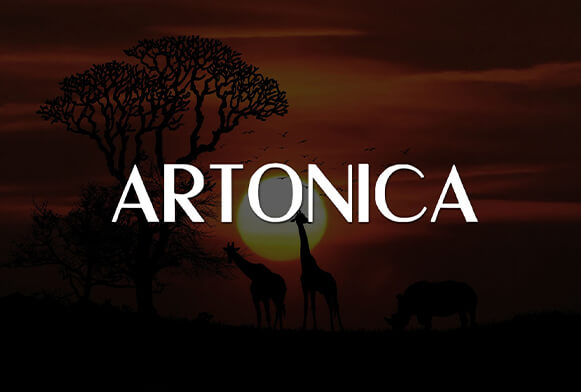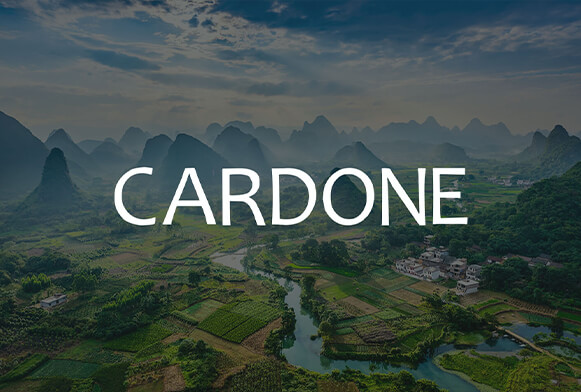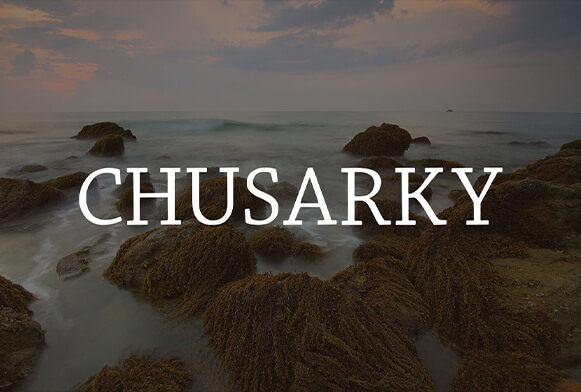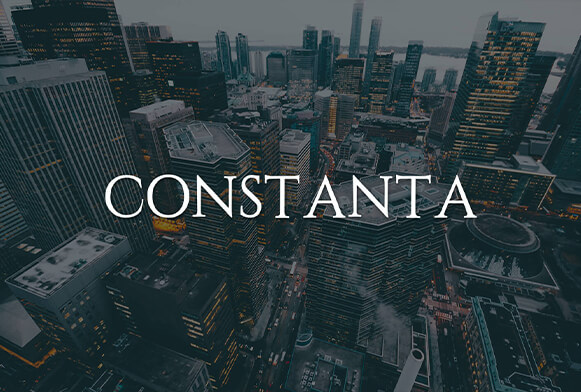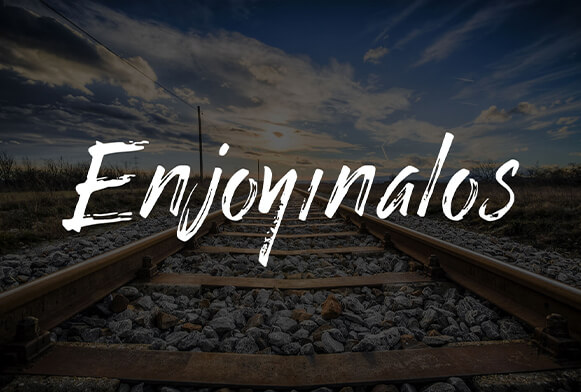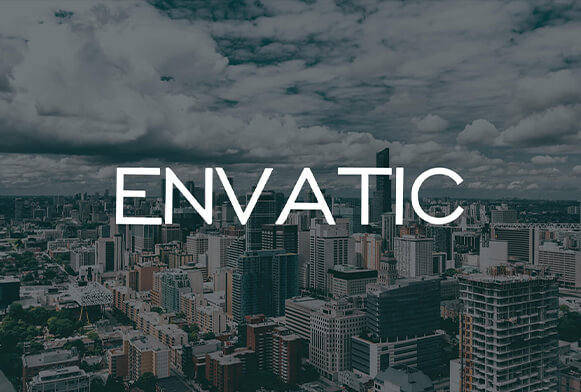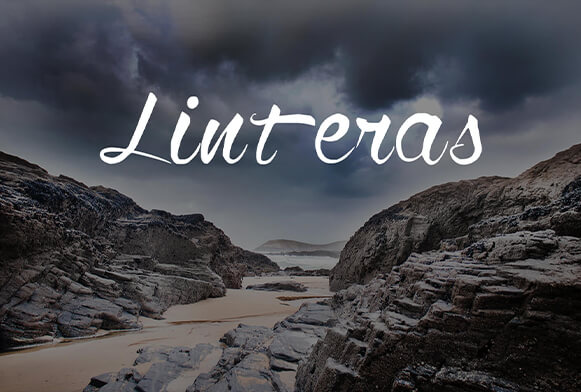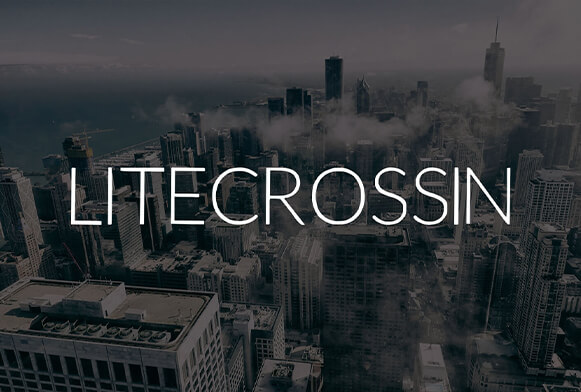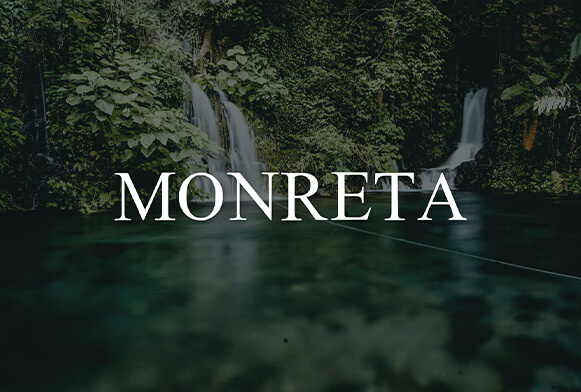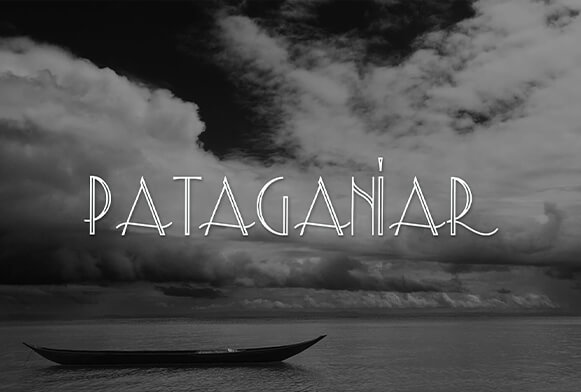
Ingyenes Photoshop betűtípusok
Ha azzal a feladattal szembesült, hogy szöveget adjon hozzá a fényképezéshez, ezek az ingyenes Photoshop-betűtípusok, amelyeket professzionális fotóretusálók készítettek, nagyon hasznosak lesznek. Ne tedd a képed tetejére az első betűtípust, amivel először találkozol, keress egy figyelemre méltó betűtípust, amely harmonikusan illeszkedik fényképezési stílusodhoz. Az Ön kényelme érdekében a FixThePhoto csapata kiválasztotta a legjobb ingyenes betűtípusokat a Photoshop számára, amelyek alkalmasak különféle típusú fotózásokhoz.
Photoshop Fonts #1 "Acimetr"
A betűtípus egyszerű, könnyen olvasható betűket tartalmaz, amelyek minden fontos üzenetet közvetítő képhez megfelelőek. Az ebből a betűk széleit serifekkel egészítik ki a kifinomult megjelenés érdekében.
Betűtípusok a Photoshop #2 "Apogear"
Ez a legjobb Photoshop betűtípus, ha azt szeretné, hogy a szöveg kiemelkedjen. A vastag és vékony vonalakat kerek örvényekkel ötvözi.
Ingyenes Photoshop Fonts #3 "Aquataken"
Még egy áttekinthető betűtípus, apró további serifekkel a széleken ebből a betűkkel. Ez egy univerzális fényképezési betűtípus, amely minden képhez biztosan illeszkedik.
Ingyenes betűtípusok a Photoshop #4 "Arcon"
Ez az egyik legjobb professzionális betűtípus, amelyet kissé hosszúra rajzolt betűk jellemeznek. Egyszerűsége miatt széles körben használják a nyomtatott médiában.
Photoshop Font #5 "Artonica"
Ez tekinthető az egyik legnagyobb, teljesen olvasható ingyenes betűtípusnak a Photoshop fotózáshoz logóihoz. A vékony és vastag vonalak, éles és lekerekített élek egybeolvadása kifinomult megjelenést kölcsönöz a szövegnek.
Photoshop Fonts Free #6 "Fancy Fonts"
Ez egy ingyenes betűtípus-generátor, amely lehetővé teszi, hogy szövegét stílusos betűtípusra formázza közvetlenül a böngészőben. Csak be kell írnia a szöveget, ki kell választania a kívánt betűtípust, és másolnia kell
Ingyenes Photoshop betűtípus #7 "Bardane"
Ha ezt a betűtípust alkalmazza a szövegére, akkor biztosan felkelti a figyelmet. A szokatlan kombináció ebből a vékony és vastag vonások, ívelt örvénylések és alkalmi vonalak a betűk belsejében, a betűkön vagy alatta minden kreatív fotóháttérbe beleolvad.
Ingyenes betűtípusok Photoshop #8 "Buke"
Ha fel kell hívnia a figyelmet a szövegre, vagy jobban láthatóvá kell tennie, ez a betűtípus tökéletes lesz. Merész és vastag betűket tartalmaz ívelt vonalvezetéssel, amelyek meglehetősen vonzóak.
Adobe Photoshop Fonts #9 "Cardone"
Az ebből a legjobb fonts Photoshop listához tartozik. Ezt a betűtípust gyakran használják olyan szövegeknél, amelyek mindenféle ebből információt kifejeznek, mert ebből a következetes betűforma és a szép megjelenés.
Photoshop ingyenes betűtípusok #10 "Carridge"
Ez az egyik legnagyobb, kézzel rajzolt ingyenes Photoshop betűstílus. Egyedülálló ívei és vonásai mindenképpen modernizálnak minden szöveget vagy címet.
Photoshop betűtípus #11 "Chalsyn"
Kiváló serif betűtípus azok számára, akik fotózás logó betűtípusokat keresnek. A betűket vékony és egyszerű vonalak jellemzik, amelyek hozzájárulnak a szöveg üdítő megjelenéséhez.
Font Photoshop #12 "Chitosa"
Ez az egyik legismertebb ecset legjobb Photoshop betűtípus. A bonyolult vonalak és örvénylések keveréke némi hangulatot ad a szöveghez.
Betűtípusok Photoshop #13 "Chusarky"
Nem tévedhetsz ezzel a serif betűtípussal, ha arra van szükséged, hogy a szöveg egészen egyszerűnek és minimalistanak tűnjön. Az ebből az átlagos vastagságú betűk tiszta vonalakkal minden képen elférnek.
PSD Fonts #14 "Constanta"
Az ebből this font név mindent elmond – az ebből állandó alakú betűk, amelyek enyhén merésznek tűnnek. Javasoljuk, hogy ezt a serif betűtípust használja címekhez, például a webhelyeken.
Photoshop betűtípus ingyenes #15 "Contaria"
Ez az egyik legmegfelelőbb ingyenes betűtípus természet- és tájképekhez. Kerek élei békét és nyugalmat kölcsönöznek az egésznek.
A Photoshop legjobb betűtípusai #16 "Dowlink"
A geometrikusan hosszú rajzolt betűket ebből a betűtípusból vékony és egyenetlen ecsetvonások egészítik ki. Alkalmazza arra az esetre, ha grunge hatást szeretne elérni ebből a szövegből.
Photoshop Font #17 " Eclipse"
Ha ingyenes betűtípusokat keres a tervezők számára, ez az egyik közülük. Finoman és finoman lekerekített élek, a változatos forgatás ebből a betűk azonnal felkeltik a figyelmet a képre és a szövegre.
Ez az egyik az Adobe Photoshop ingyenes betűtípusai közül, amelyek első pillantásra hétköznapinak tűnhetnek. Valójában azonban van egy bizonyos varázsa az egyszerűségében és a kis örvénylésekben, amelyek feltűnőek lehetnek, ha a betűtípust megfelelően alkalmazzák.